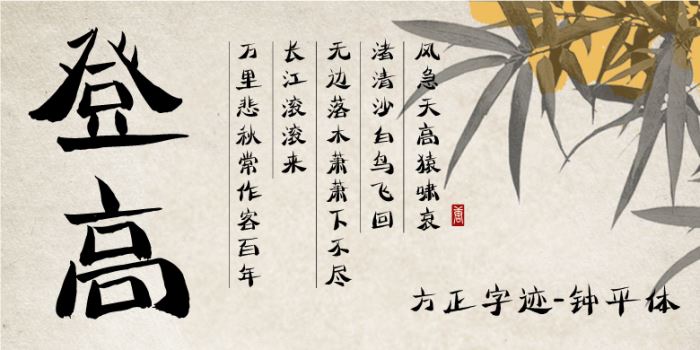
方正字跡-鐘平體由方正字庫(kù)張鐘平設(shè)計(jì)師出品的藝術(shù)字體,字體字體為上窄下寬,左低右高形狀,上部筆畫尖細(xì)、挺拔直穿云霄,下部字體寬博厚重、承載萬(wàn)物,適合應(yīng)用于藝術(shù)設(shè)計(jì)、平面宣傳設(shè)計(jì)、網(wǎng)頁(yè)設(shè)計(jì),書法等領(lǐng)域。
字體為上窄下寬,左低右高形狀,上部筆畫尖細(xì)、挺拔直穿云霄,下部字體寬博厚重、承載萬(wàn)物,具有天高地闊、恢弘大氣之象。